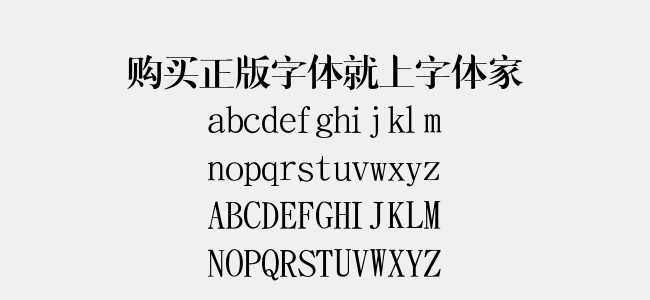
金梅梯形变形字体.TTF
金梅梯形变形字体.TTF是一款非常漂亮的艺术字体,金梅梯形变形字体.TTF字体广泛用于各种书刊、画册的设计印刷中,金梅梯形变形字体.TTF字体具有强烈的视觉冲击力,报纸和杂志和书籍中常用字体, 海报、个性促进品牌标志设计、字体设计、等环境。
金梅梯形变形字体.TTF是一款非常漂亮的艺术字体,金梅梯形变形字体.TTF字体广泛用于各种书刊、画册的设计印刷中,金梅梯形变形字体.TTF字体具有强烈的视觉冲击力,报纸和杂志和书籍中常用字体, 海报、个性促进品牌标志设计、字体设计、等环境。 金梅梯形变形字体.TTF字体是一款用于标题设计方面的字体,由字体下载站提供免费下载,字体下载大全提供最全最新的中、英文字体素材。